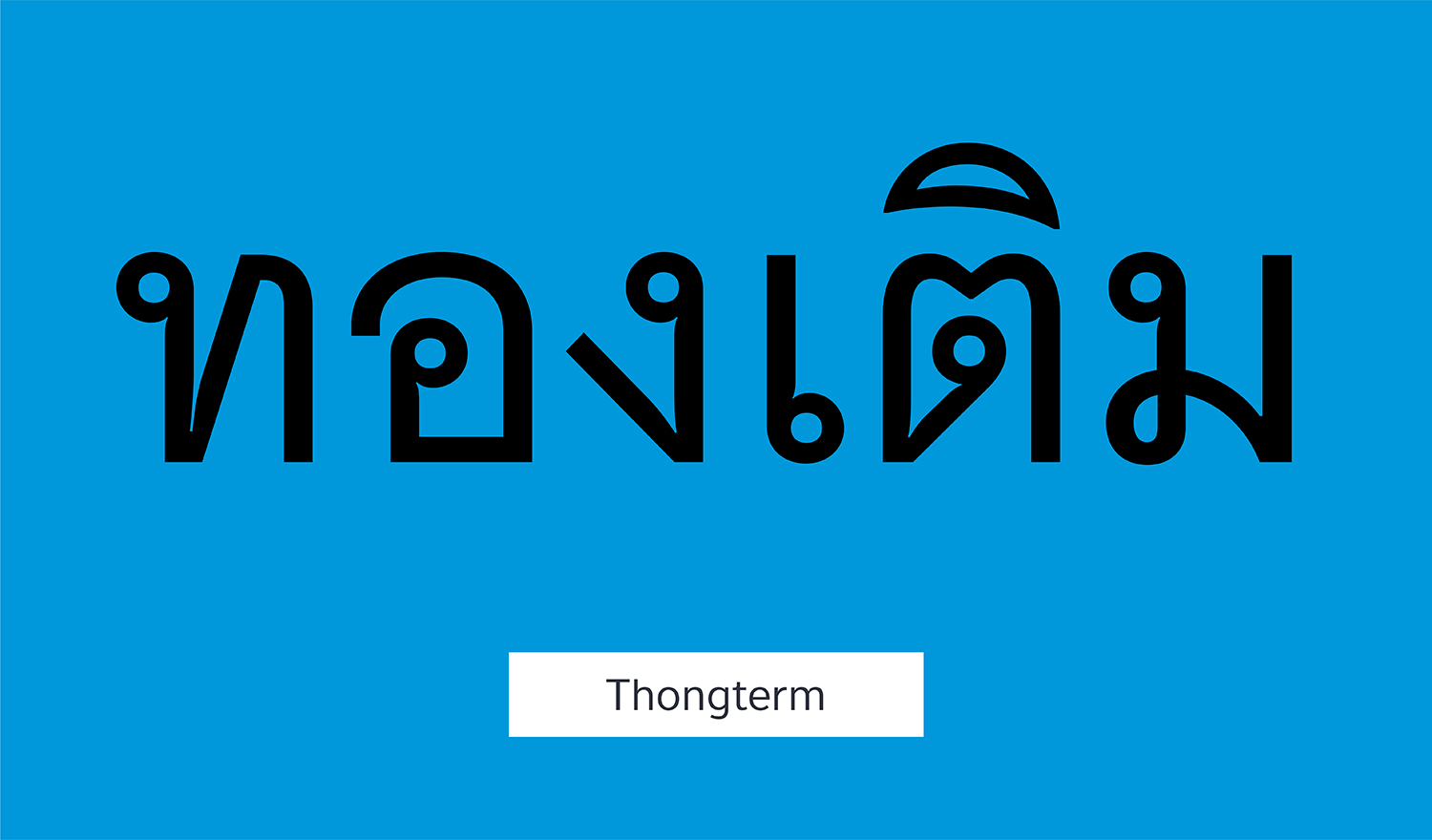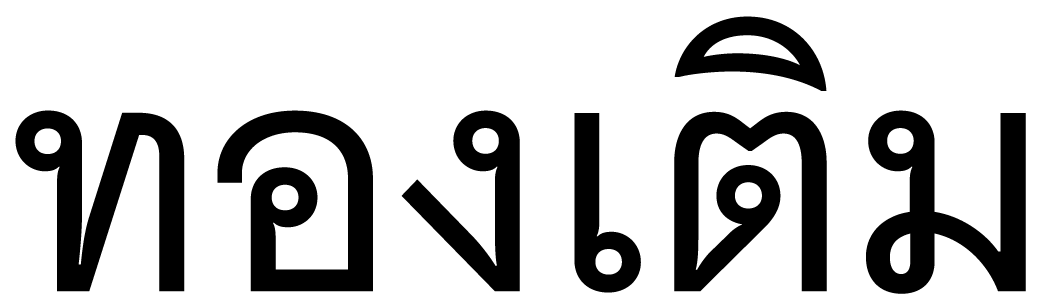
Thongterm
통텀은 카싼디막 컬렉션에서 가장 인기있는 본문용 폰트 중 하나입니다. 통텀은 장시간의 읽기를 목적으로 하여 중립적이고 격식있는 텍스트면을 제공합니다. 이는 사진식자 시대에 사용되었던 보편적인 신문용 폰트에 기반한 디자인을 가지고 있습니다. 만약 가장 보편적인 태국어 폰트를 찾는다면, 통텀을 가장 안전하고 기본적인 유형으로 선택하실 수 있습니다.
이제 통텀을 베트남어로도 사용하실 수 있습니다!